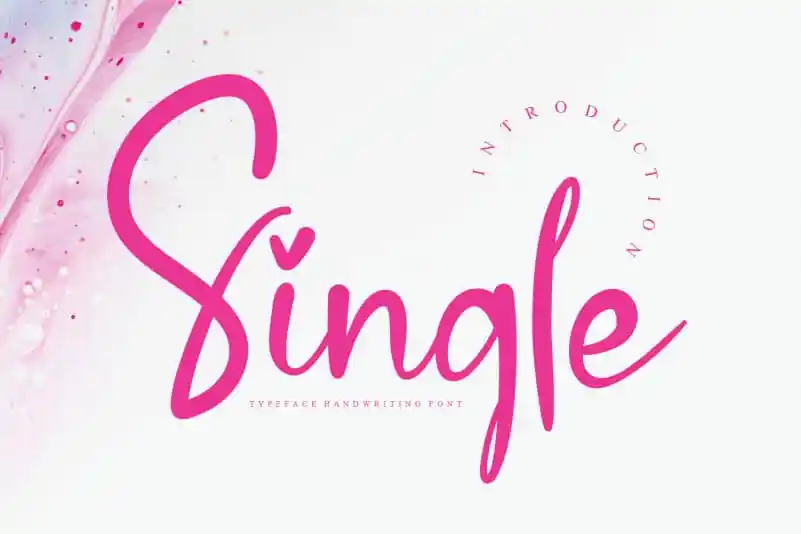
Esta página de download apresenta a ‘Single Script Font’, uma seleção cuidadosamente selecionada de fótons manuscritos criativos produzidos pelo Designer creativeletter. A fonte é perfeita para aqueles que buscam uma experiência única e detalhada, oferecendo um toque pessoal em qualquer projeto onde seja usada. Com a ‘Single Script Font’, os designers podem experimentar diferentes estilos de escrita manuscrita, criando textos emocionantes e distintos. As linhas delicadas e os traços fluidos do design permitem ao usuário expressar sua personalidade através da escrita, tornando cada projeto único. O estilo manuscrito oferecido pela ‘Single Script Font’ é ideal para a criação de materiais de marketing, editoriais ou qualquer projeto que valorize uma experiência autêntica e pessoal. Essa fonte representa um acréscimo valioso à sua coleção de recursos gráficos, proporcionando aos criativos novas maneiras de explorar a expressão através da escrita.